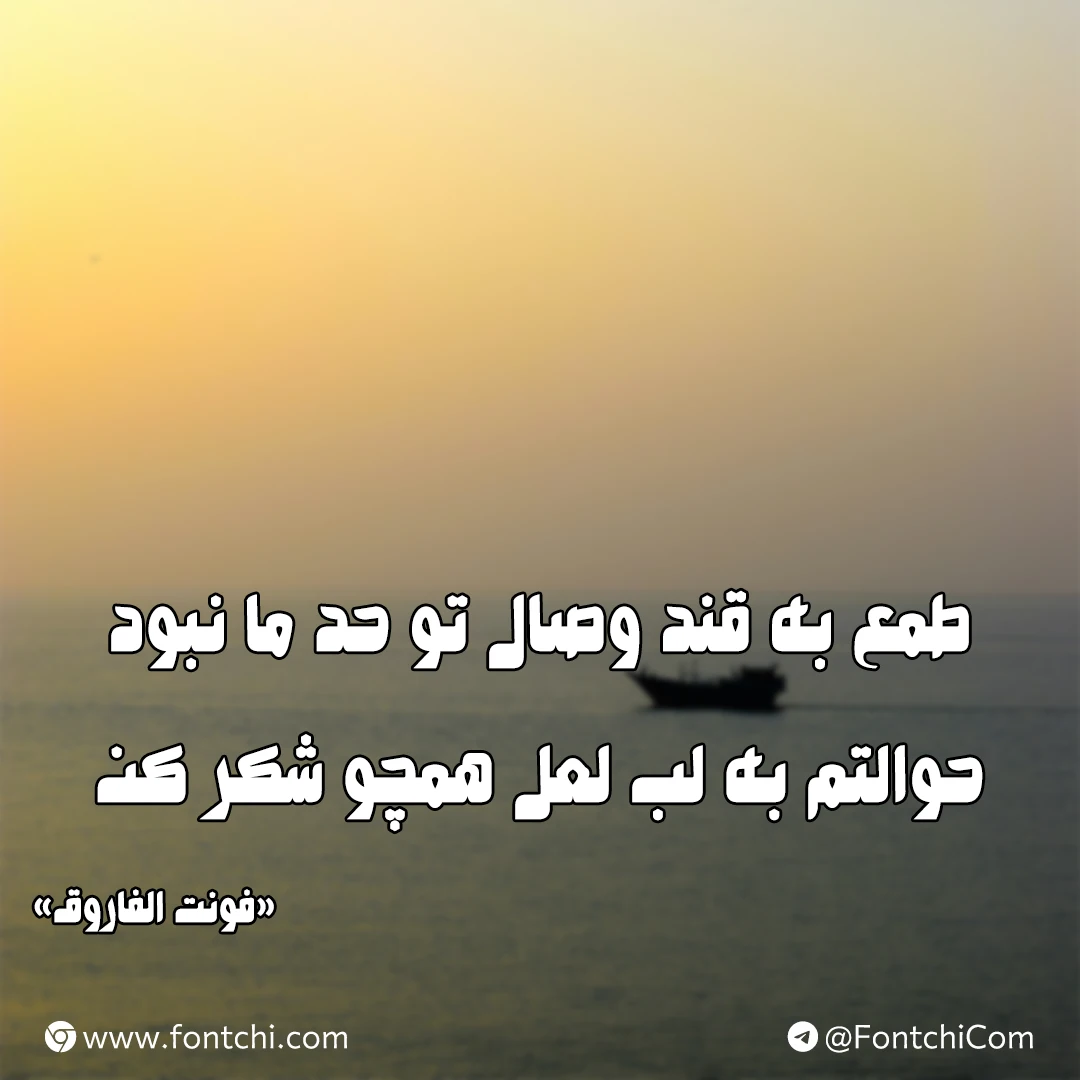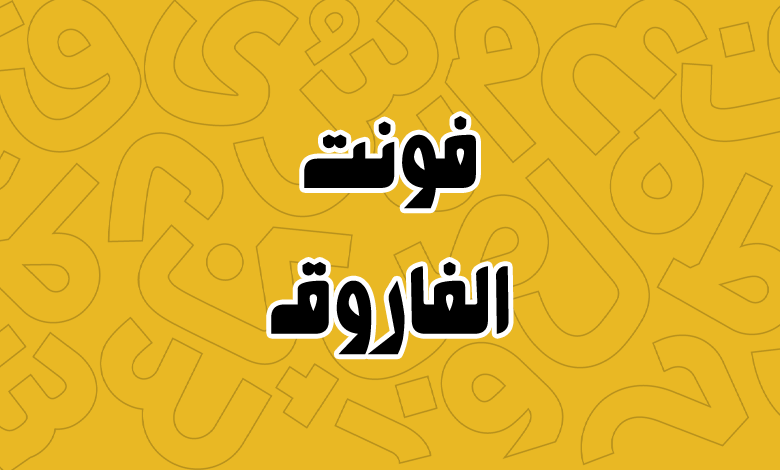
فونت الفاروق (Alfarooq)
فونت الفاروق یا فونت عربی فاروق (به انگلیسی: Alfarooq) یک فونت عربی است که از حروف فارسی «گ، چ، پ، ژ» نیز پشتیبانی میکند. این فونت که ظاهری گرافیکی و فانتزی دارد برای استفاده در عناوین، تیترها و متون کوتاه مناسب است.
فونت فاروق از یک وزن معمولی Regular پشتیبانی میکند. اما برخلاف عنوانش، دارای وزنی بولد و نسبتا سیاه است. استفاده از این فونت برای کارهایی که نیاز به جلب توجه مخاطب و ظاهر نمایشی داشته باشید توصیه میشود.
فونت عربی فاروق محدود به این زبان نیست و میتوانید برای زبان فارسی هم از این فونت استفاده کنید. اما بر خلاف استاندارد اعداد «۰۴۵۶» این فونت فارسی نبوده و به صورت عربی «۰۴۵۶» تایپ خواهند شد. همچنین این فونت فاقد گلیفهای انگلیسی بوده و برای زبان لاتین باید از فونت انگلیسی جایگزین استفاده کنید.
فاروق فونتی با ظاهر فانتزی است که برای استفاده در پوسترهای تبلیغاتی، تابلوهای سردر مغازه، صفحه آرایی کتابها و مجلات بهویژه در عناوین، تامنیل پست و ویدئوهای شبکههای اجتماعی مناسب است.